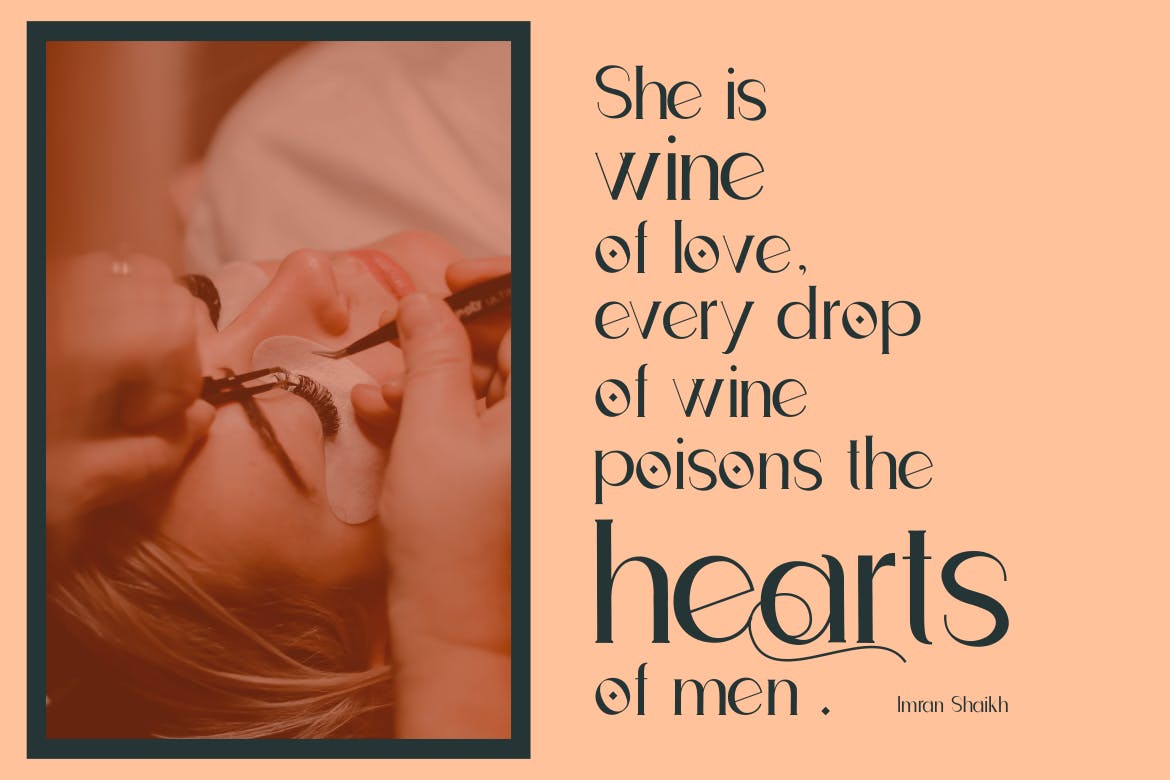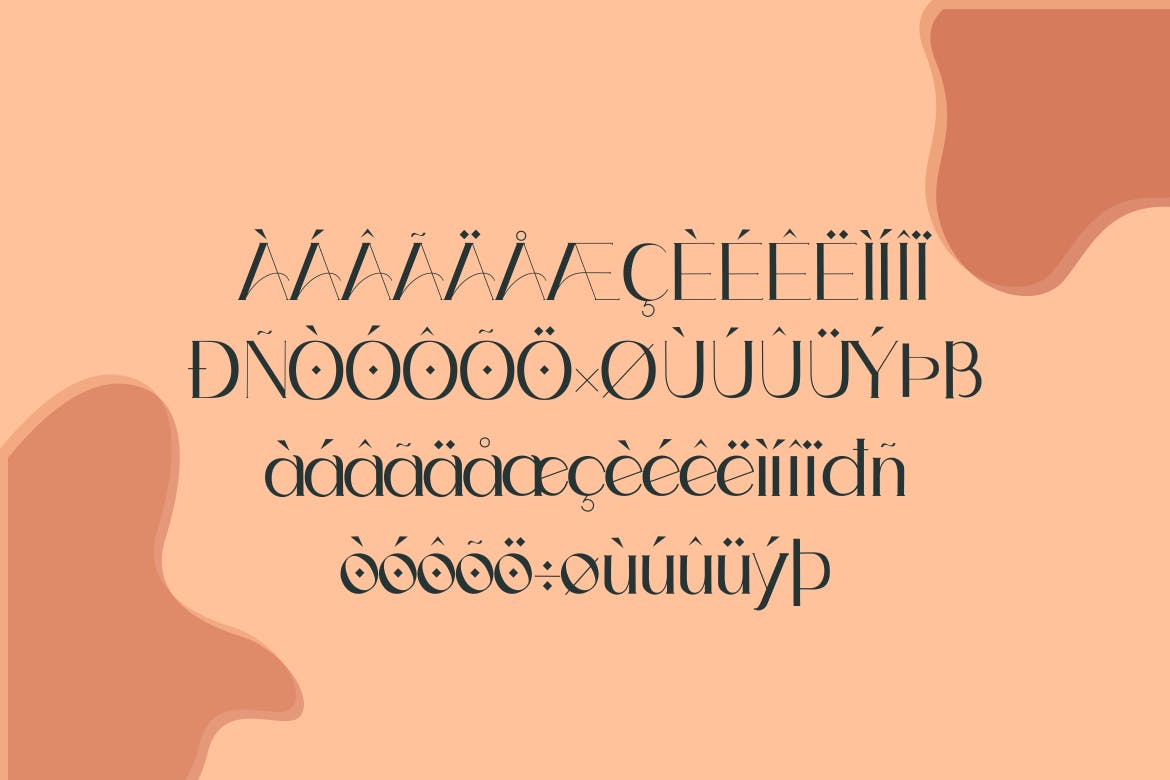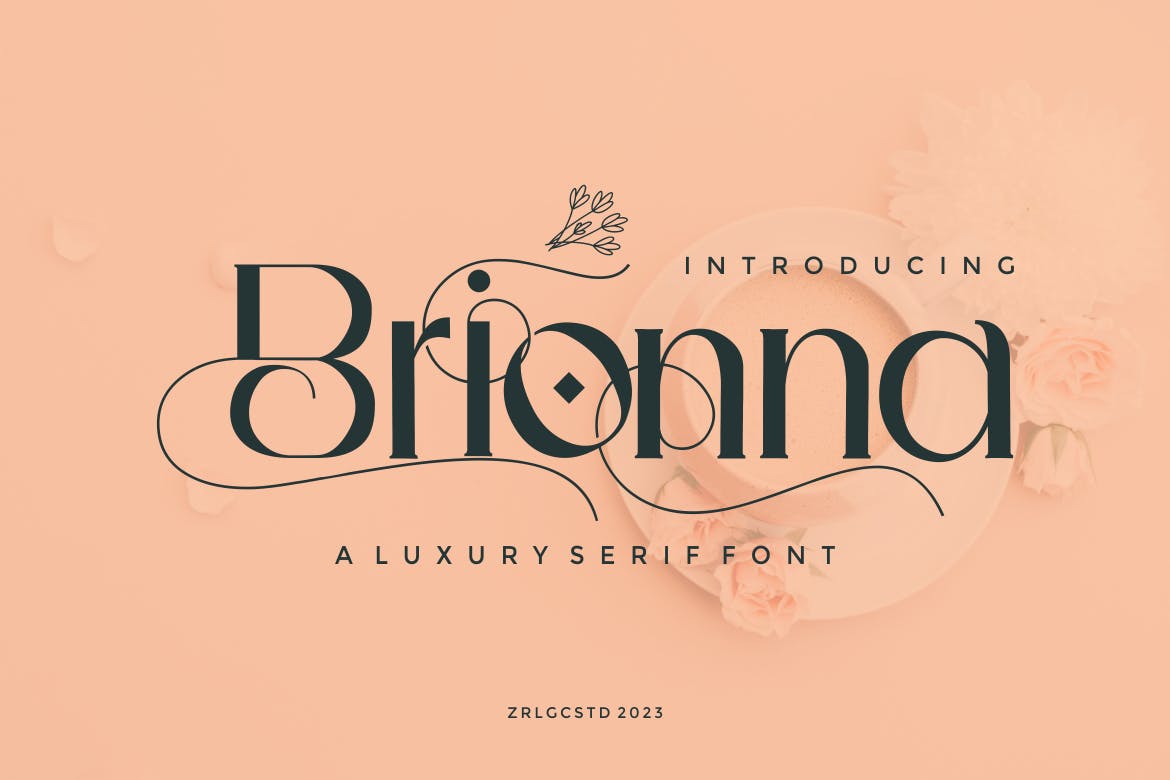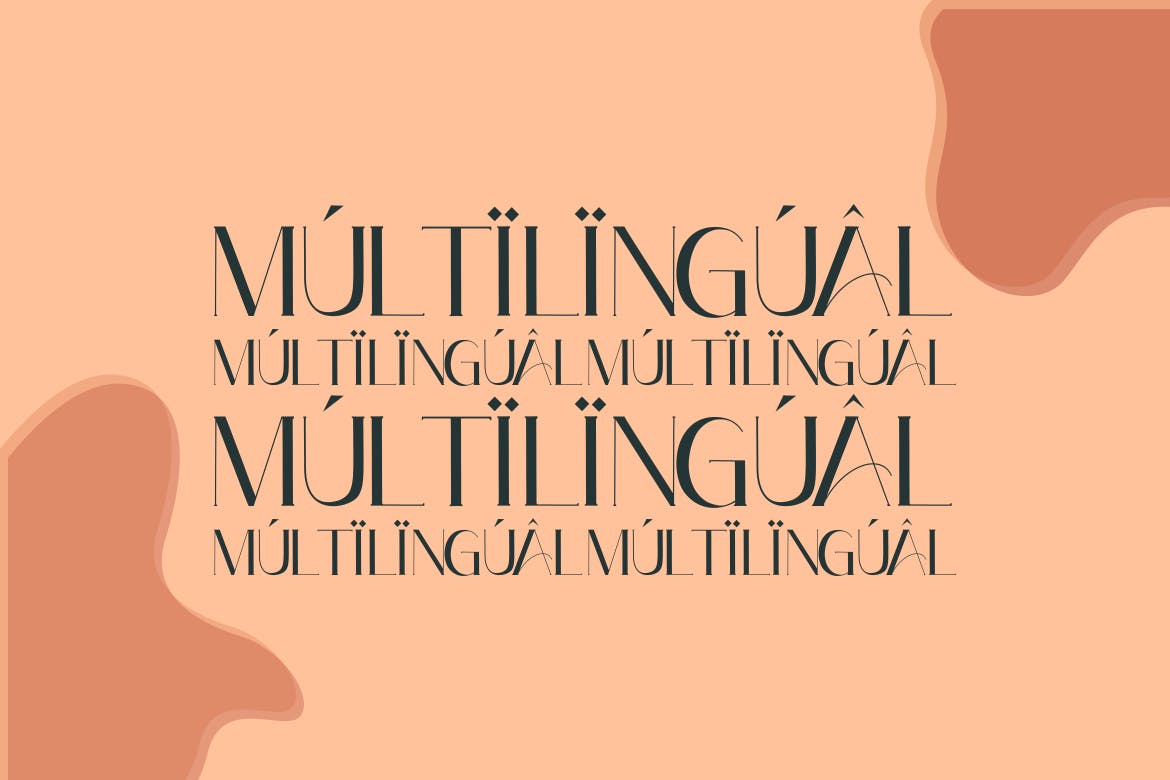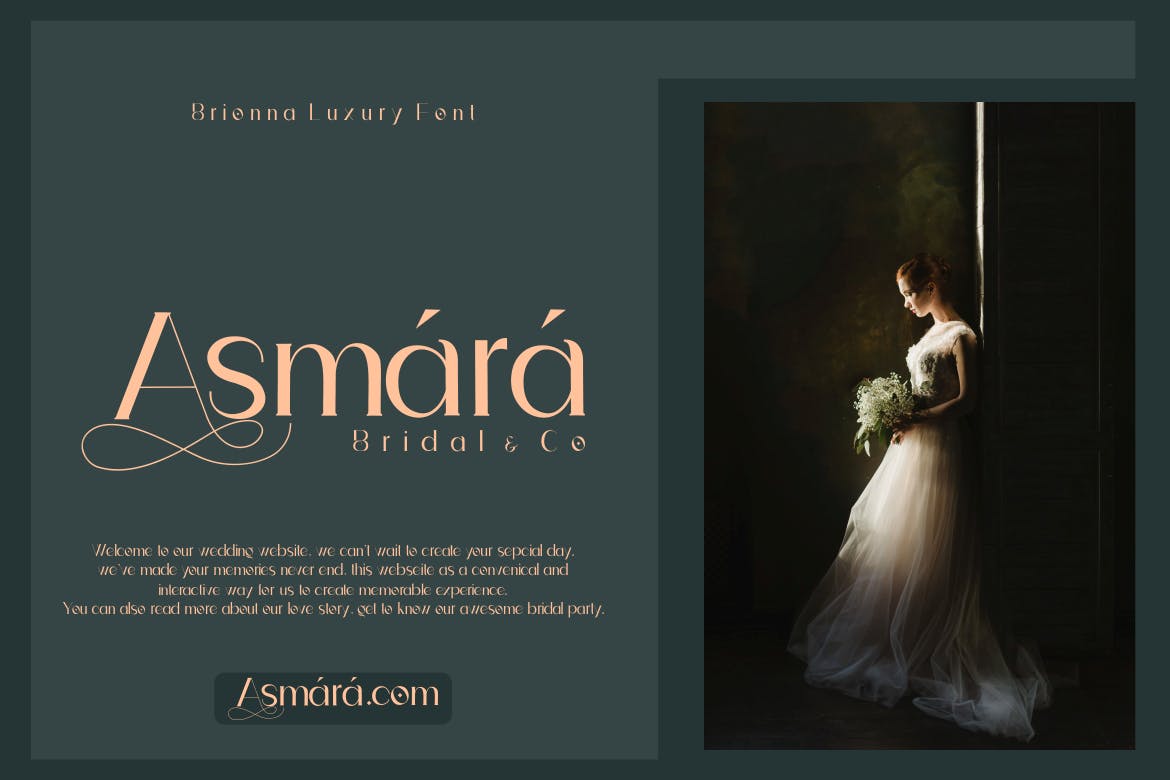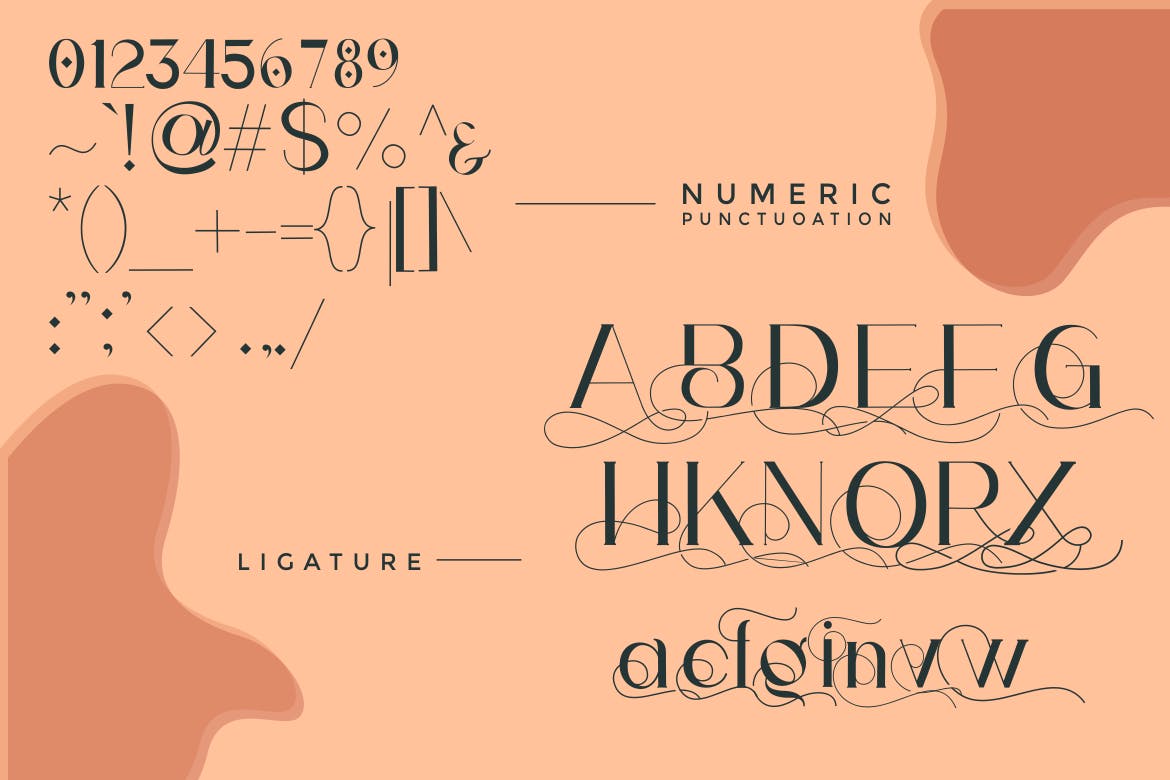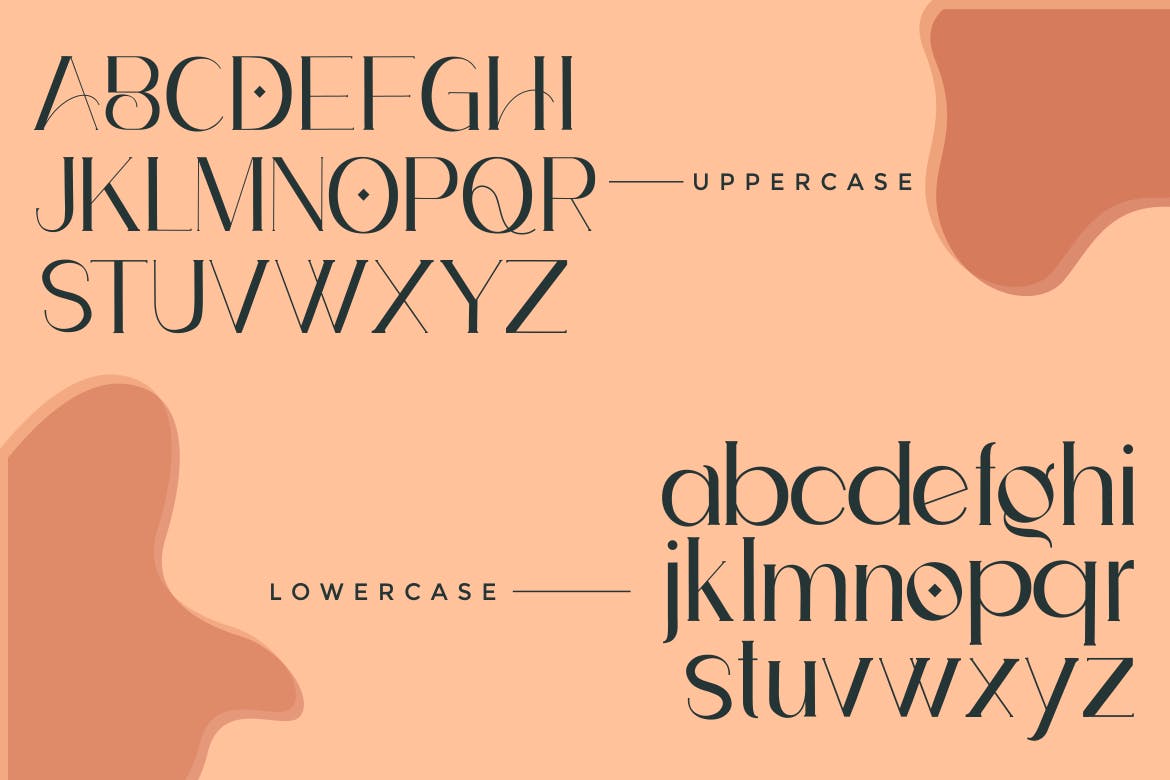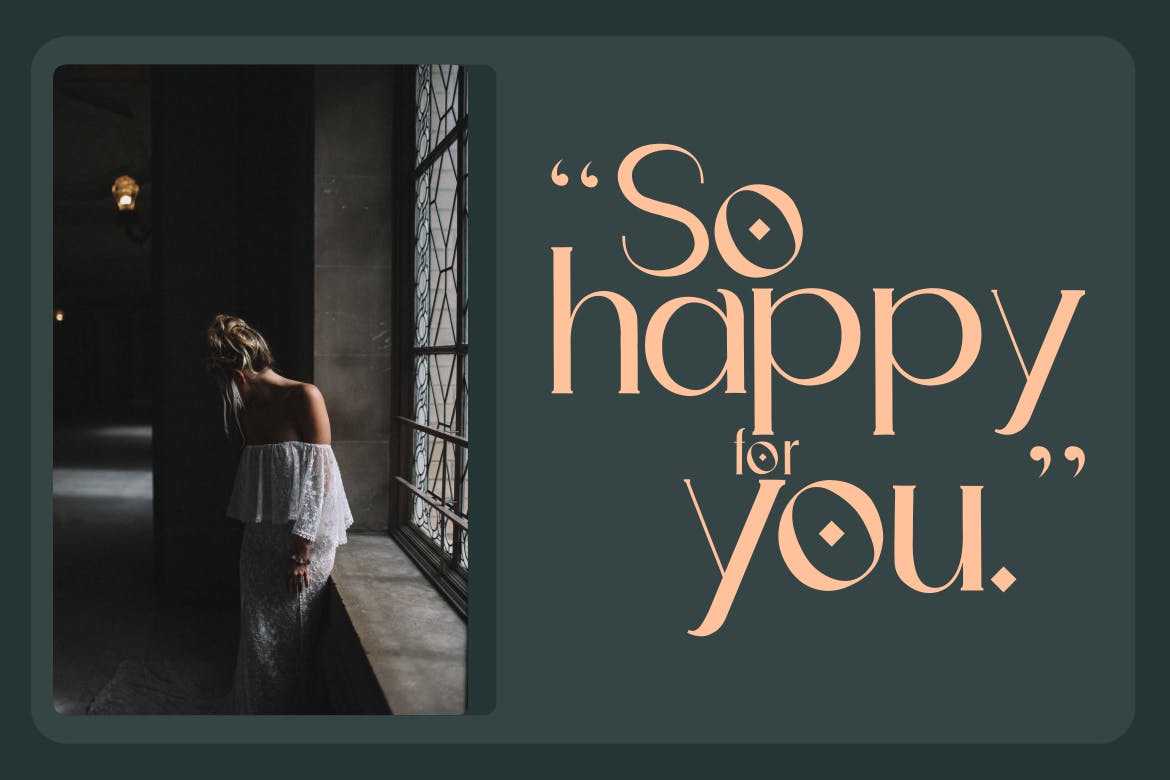
فونت Brionna یک فونت سریف مدرن و لوکس است که با طراحی خاص خود برای نیازهای شما ایجاد شده است. این فونت جذاب شامل حروف بزرگ، حروف کوچک، اعداد و نمادها میباشد. این فونت بسیار قوی و تیز، برای عناوین، تایپوگرافی، پوسترها، مجلات، بروشورها، بستهبندی، وبسایتها و بسیاری دیگر از نیازهای طراحی شما مناسب است و طراحیهای شما را جذابتر میکند.